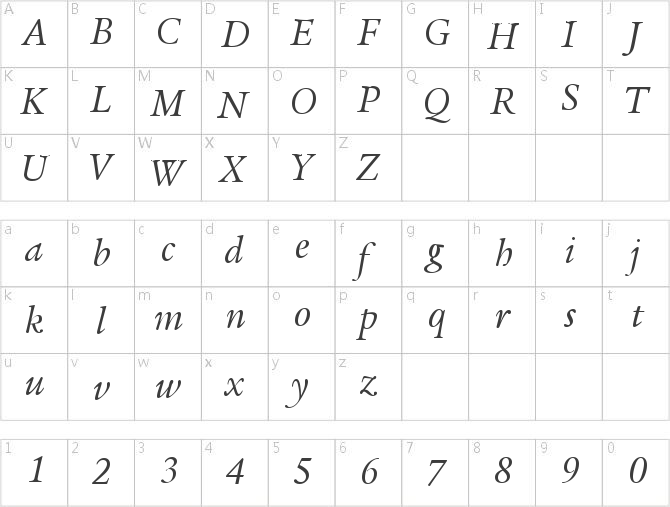
Legacy-Serif-ITC-TT-BookItalic 詳情頁
Legacy-Serif-ITC-TT-BookItalic字體字庫是一款讓人賞心悅目、百看不厭的英文字體,適合各類廣告和產品包裝設計應用,字體大小0.07MB,格式為ttf字體,上傳用戶是Me / ,yD ,作者/版權方為未知